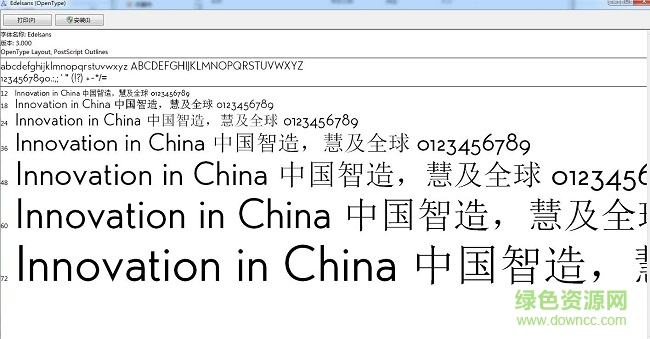
edelsans字體是一款美觀大方的標(biāo)準(zhǔn)無(wú)襯線字體,結(jié)構(gòu)工整,點(diǎn)畫呼應(yīng),給人的視覺(jué)印象非常清晰干凈,比較符合審美,需要的朋友快來(lái)下載吧?。?/p>
可廣泛應(yīng)用于宣傳、廣告、商標(biāo)、標(biāo)語(yǔ)、黑板報(bào)、企業(yè)名稱、會(huì)場(chǎng)布置、展覽會(huì), 以及商品包裝和裝潢,各類廣告、報(bào)刊雜志和書籍的裝帖上等!